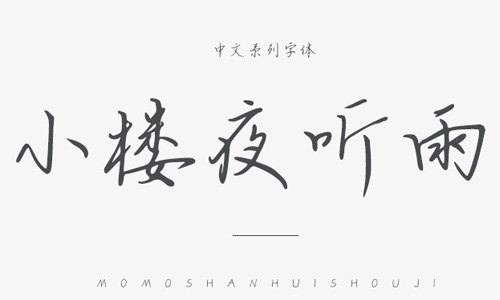
小樓夜聽雨字體是一款具有硬筆手寫效果的中文藝術(shù)字體,同時(shí)又頗有一種草書的感覺,整體效果不拘章法,象征著自由,可以廣泛應(yīng)用于廣告設(shè)計(jì)、宣傳海報(bào)、ppt、影視制作以及任何使用文字的領(lǐng)域,歡迎有興趣的朋友們前來下載使用。
我獨(dú)坐山外小閣樓,酌一杯美酒,聽一夜細(xì)雨,念一夜相思。——小樓夜聽雨。本字體是在國家標(biāo)準(zhǔn)簡(jiǎn)體字庫GB2312所包含6763漢字的基礎(chǔ)上,又增加了近200常用字,已經(jīng)覆蓋了大陸99.75%的漢字使用頻率,足以滿足日常需求。